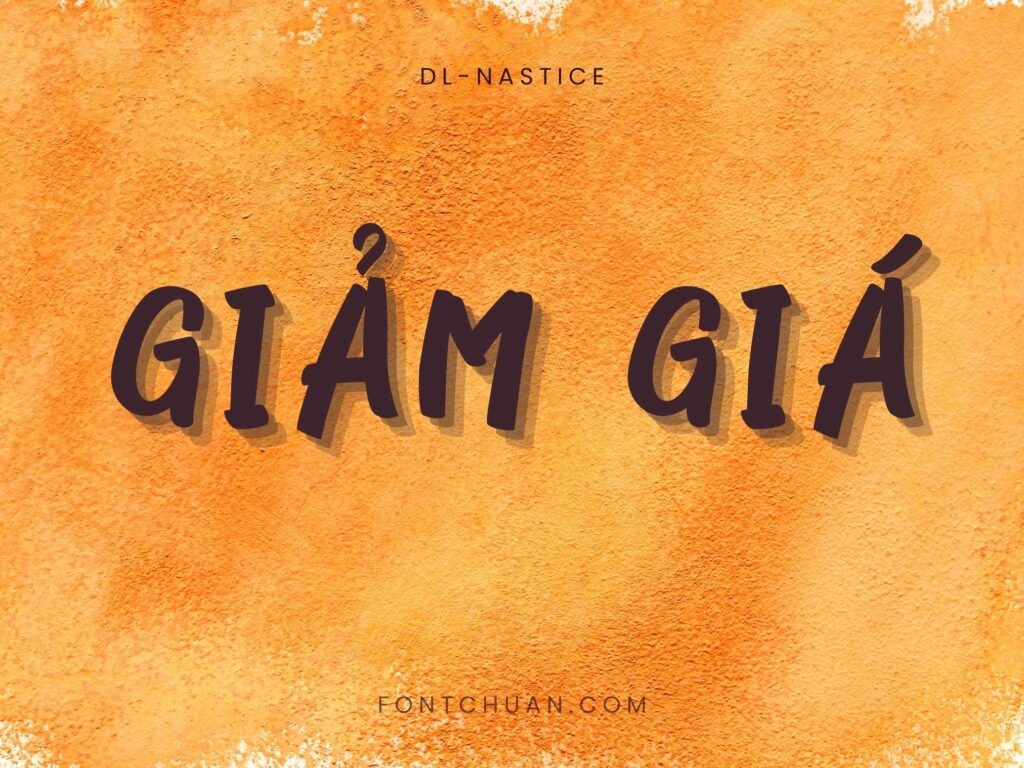
Font DL Nastice Việt Hóa
Nastice là một phông chữ viết tay với phong cách cọ vẽ độc đáo, được thiết kế bởi Typecase. Phông chữ này mang lại cảm giác tự nhiên và năng động, phù hợp cho các thiết kế như logo, nhãn tên, trích dẫn viết tay, bao bì sản phẩm, hàng hóa, truyền thông xã hội và thiệp chúc mừng. Với những nét cọ phóng khoáng và hiệu ứng vẽ tay mạnh mẽ, Nastice cũng có thể được sử dụng như một Font chữ Halloween, giúp tạo điểm nhấn ấn tượng và sinh động cho các thiết kế chủ đề lễ hội hoặc sự kiện đặc biệt. Nastice bao gồm bộ chữ cái in hoa, dấu câu, số và hỗ trợ đa ngôn ngữ. Phông chữ này miễn phí cho sử dụng cá nhân; nếu bạn muốn sử dụng cho mục đích thương mại, vui lòng mua giấy phép thương mại từ tác giả. Bạn có thể tải phông chữ này từ trang web dafont.com.